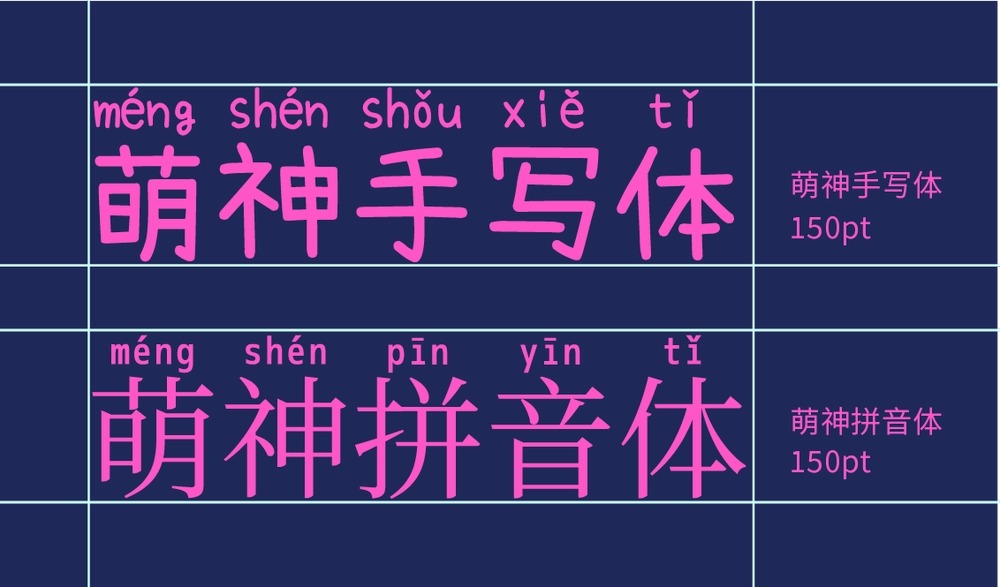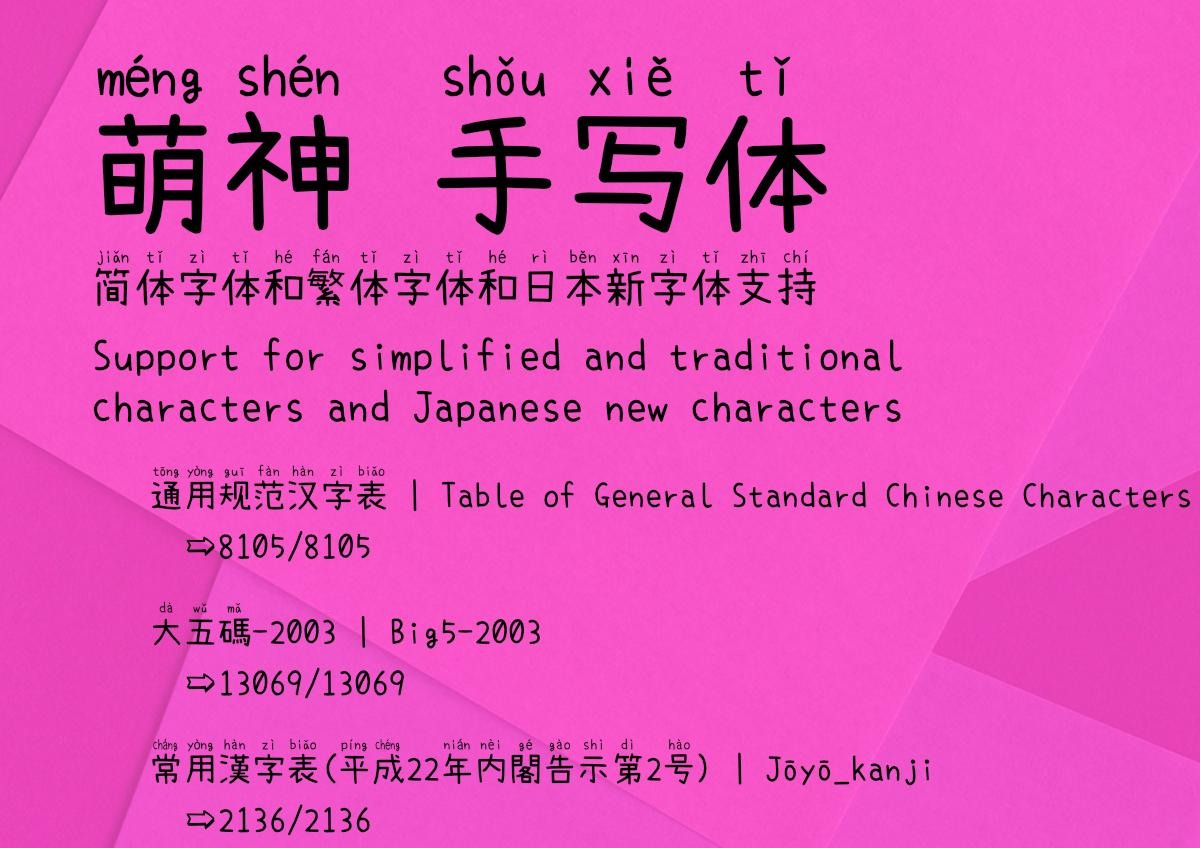
萌神手写体(Mengshen-Handwritten)是基于开源字体小赖字体改造而成,专为中文学习设计的一款免费商用字体。
字体在保留小赖字体的基础结构上融入了拼音设计,使其在输出汉字时会自动标注汉语拼音,而且是简繁均带拼音,很适合儿童或外国人中文启蒙。但与萌神拼音体不同的是,萌神手写体的笔画较为圆润,整体风格也比较可爱,所以更适合儿童教育、绘本、手账、创意海报等设计场景。
两种字体对比如下:
| 项目 | 萌神手写体 | 萌神拼音体 |
|---|
| 基底字体 | 小赖字体(原子笔手写) | 思源宋体(印刷体) |
| 风格气质 | 圆润、软萌、卡通、手写感 | 工整、清晰、正式、宋体衬线 |
| 笔画 | 粗细均匀、柔和、无衬线 | 横细竖粗、有衬线、结构严谨 |
| 拼音位置 | 字上方,自动显示 | 字上方,自动显示 |
| 多音字 | 支持智能切换 | 支持 |
| 阅读感 | 活泼、可爱、适合短句 | 舒适、适合长文、教科书级 |
| 字符数量 | 极多 (约3.3万,含日韩汉字) | 多 (基于思源,简繁支持好) |
| 最佳用途 | 早教、儿童、文创、萌系设计 | 教材、教辅、正式学习、长文 |